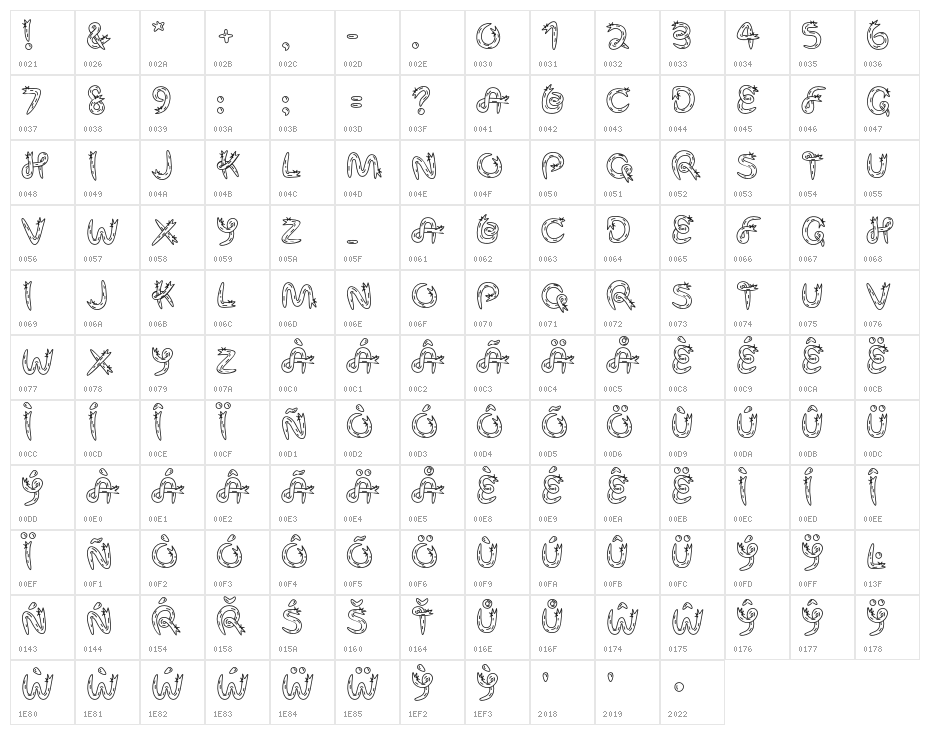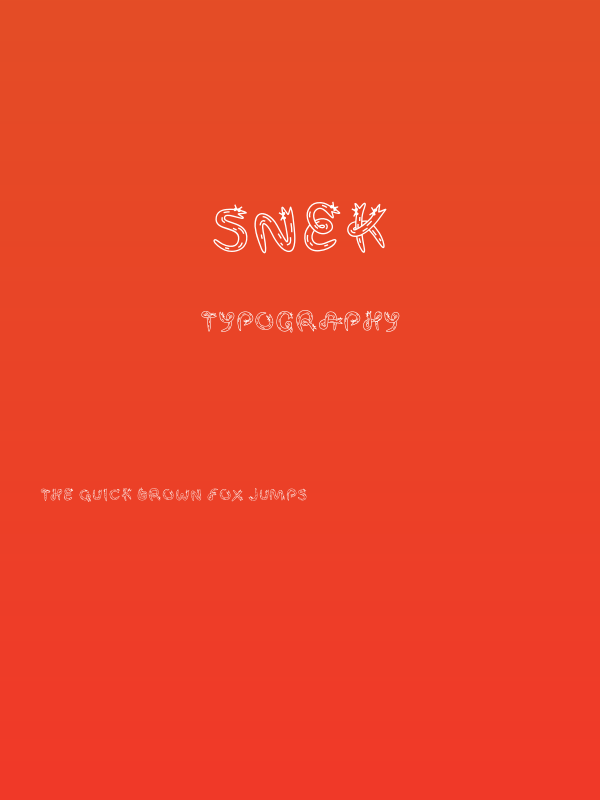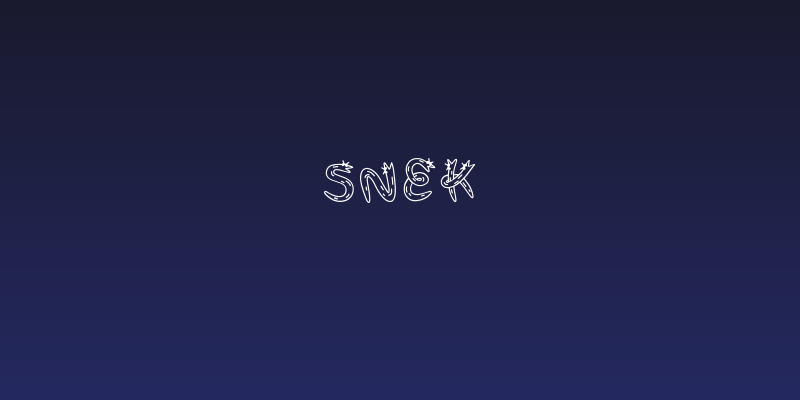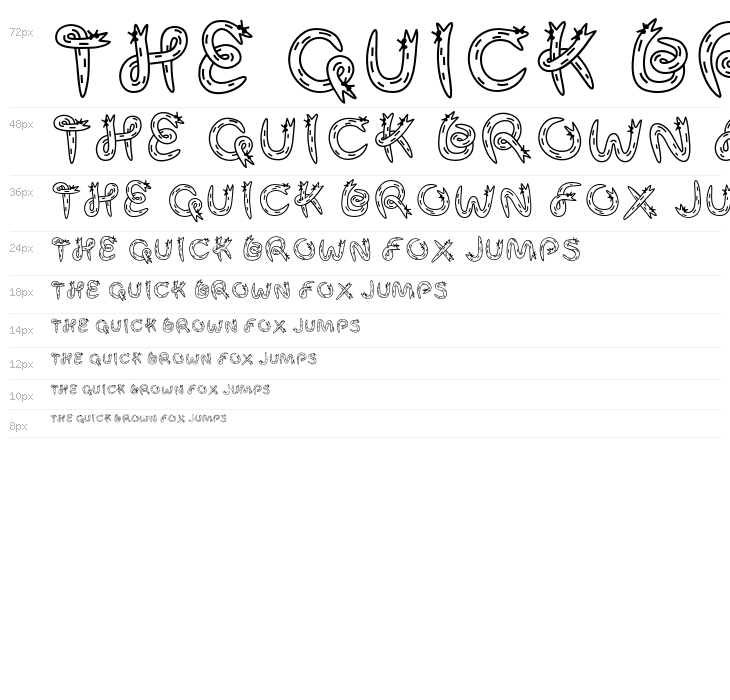
Snek Font
| Vorgeschlagene Projekte | Ideal for children's book covers, playful branding, themed event invitations, or any project requiring a fun and eye-catching typeface. |